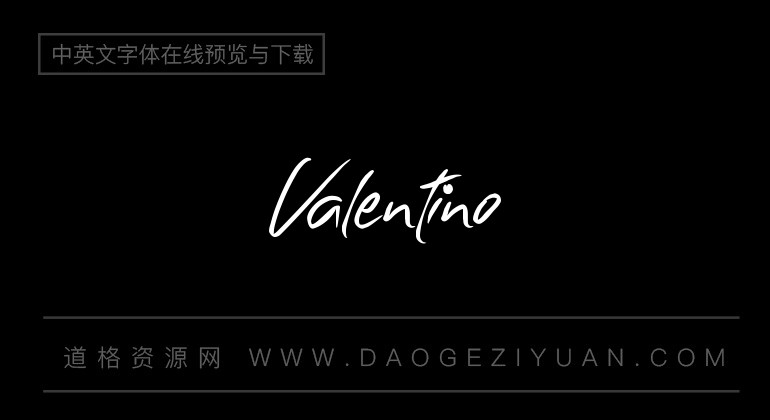
Valentino
Valentino 字体是一款由 typefoundry 创建的手写字体,它的特点是简单而优雅。它有着优美的曲线,细腻的折痕,以及柔和的笔触,使其具有独特的风格。它适用于各种类型的文字,并且可以用于不同的项目,例如海报,书籍,T恤,和更多。
Valentino是一款非常不错的手写艺术字体,具有很好的视觉感,适合于文化类的宣传设计、商业类品牌的广告和产品包装设计以及个性化文字排版等较多场景。